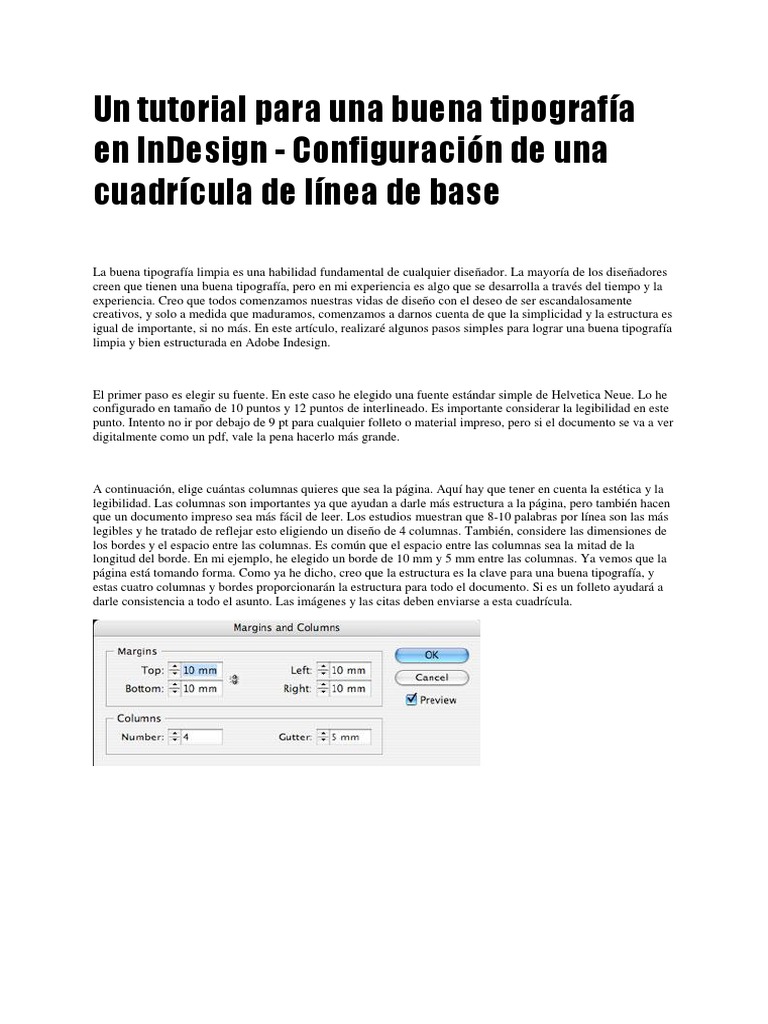
Un tutorial para una buena tipografía
en InDesign - Configuración de una
cuadrícula de línea de base
La buena tipografía limpia es una habilidad fundamental de cualquier diseñador. La mayoría de los diseñadores
creen que tienen una buena tipografía, pero en mi experiencia es algo que se desarrolla a través del tiempo y la
experiencia. Creo que todos comenzamos nuestras vidas de diseño con el deseo de ser escandalosamente
creativos, y solo a medida que maduramos, comenzamos a darnos cuenta de que la simplicidad y la estructura es
igual de importante, si no más. En este artículo, realizaré algunos pasos simples para lograr una buena tipografía
limpia y bien estructurada en Adobe Indesign.
El primer paso es elegir su fuente. En este caso he elegido una fuente estándar simple de Helvetica Neue. Lo he
configurado en tamaño de 10 puntos y 12 puntos de interlineado. Es importante considerar la legibilidad en este
punto. Intento no ir por debajo de 9 pt para cualquier folleto o material impreso, pero si el documento se va a ver
digitalmente como un pdf, vale la pena hacerlo más grande.
A continuación, elige cuántas columnas quieres que sea la página. Aquí hay que tener en cuenta la estética y la
legibilidad. Las columnas son importantes ya que ayudan a darle más estructura a la página, pero también hacen
que un documento impreso sea más fácil de leer. Los estudios muestran que 8-10 palabras por línea son las más
legibles y he tratado de reflejar esto eligiendo un diseño de 4 columnas. También, considere las dimensiones de
los bordes y el espacio entre las columnas. Es común que el espacio entre las columnas sea la mitad de la
longitud del borde. En mi ejemplo, he elegido un borde de 10 mm y 5 mm entre las columnas. Ya vemos que la
página está tomando forma. Como ya he dicho, creo que la estructura es la clave para una buena tipografía, y
estas cuatro columnas y bordes proporcionarán la estructura para todo el documento. Si es un folleto ayudará a
darle consistencia a todo el asunto. Las imágenes y las citas deben enviarse a esta cuadrícula.
Así que hemos configurado una cuadrícula verticalmente, el siguiente paso será configurar una cuadrícula
horizontal o de línea base, en la que se mantendrá todo nuestro texto. Este es un factor clave para una buena
tipografía e InDesign es una gran parte del software, ya que cuenta con todas las herramientas para simplificar
este proceso. Ya hemos elegido nuestro interlineado (12 puntos), así que configuraremos una cuadrícula para
reflejar esto. Vaya al menú de la barra superior InDesign> Preferencias> Cuadrícula. Este cuadro de menú
debería mostrar.
Arranca la rejilla a 10mm de acuerdo con tus bordes. Escriba en el cuadro Incrementar cada, 12 puntos de
acuerdo con su tipo de interlineado. Presiona OK. La cuadrícula ahora está configurada, para hacerla visible,
vaya al menú de la barra superior nuevamente, Ver> Cuadrículas y Guías> Mostrar cuadrícula de línea de base.
Ahora verá guías que se ejecutan en la página horizontalmente en la misma dirección que su tipo. Ahora haz que
tu tipo se adhiera a la cuadrícula. Abra el cuadro de visualización de párrafos, Ventana> Tipo y Tablas> Párrafo.
Seleccione el cuadro de tipo y haga clic en el botón Alinear con la cuadrícula de línea de base en la esquina
inferior derecha. Todas las líneas de tipo ahora deberían pegarse perfectamente a sus líneas de cuadrícula. Todos
los tipos adicionales que insertaremos a partir de ahora también se harán para alinearse con esta cuadrícula.
Ahora añadiremos un encabezado. La clave aquí es configurar el interlineado para que se alinee bien con nuestra
cuadrícula de base ya configurada. He puesto mi título en 95pt con un interlineado de 72pt. Básicamente, he
logrado que el interlineado sea el múltiplo de 12 puntos a los que ya está configurada nuestra red de referencia.
De esta manera, cada línea puede alinearse naturalmente con una línea del texto del cuerpo. El tamaño del título
también le permite sentarse bien y no superponerse en absoluto. Si la parte superior de las letras como h está
golpeando una curva más baja de una g, puede reducir la legibilidad y también hacerla fea. No olvide volver a
hacer clic en el botón Alinear con la cuadrícula de línea de base en el cuadro de formateo del párrafo. También
seleccione un ajuste de texto para que el texto no se superponga al encabezado sino que fluya alrededor de él.
Debería verse algo como esto.
Ahora añadiré un párrafo de introducción exactamente de la misma manera. Esta vez seleccionaré 24pt inicial,
de nuevo un múltiplo de nuestra cuadrícula 12pt. Alinéelo a la cuadrícula y debería verse algo como esto...
Como puede ver, todo se alinea perfectamente, lo que le da a la página una sensación estructurada y ordenada.
En la mayoría de los casos, trato de mantener la alineación consistente, pero en este caso he sido un poco
creativo e hice que la introducción y el título estuvieran alineados correctamente para adherirse al párrafo del
texto del cuerpo y dar una línea central nítida.